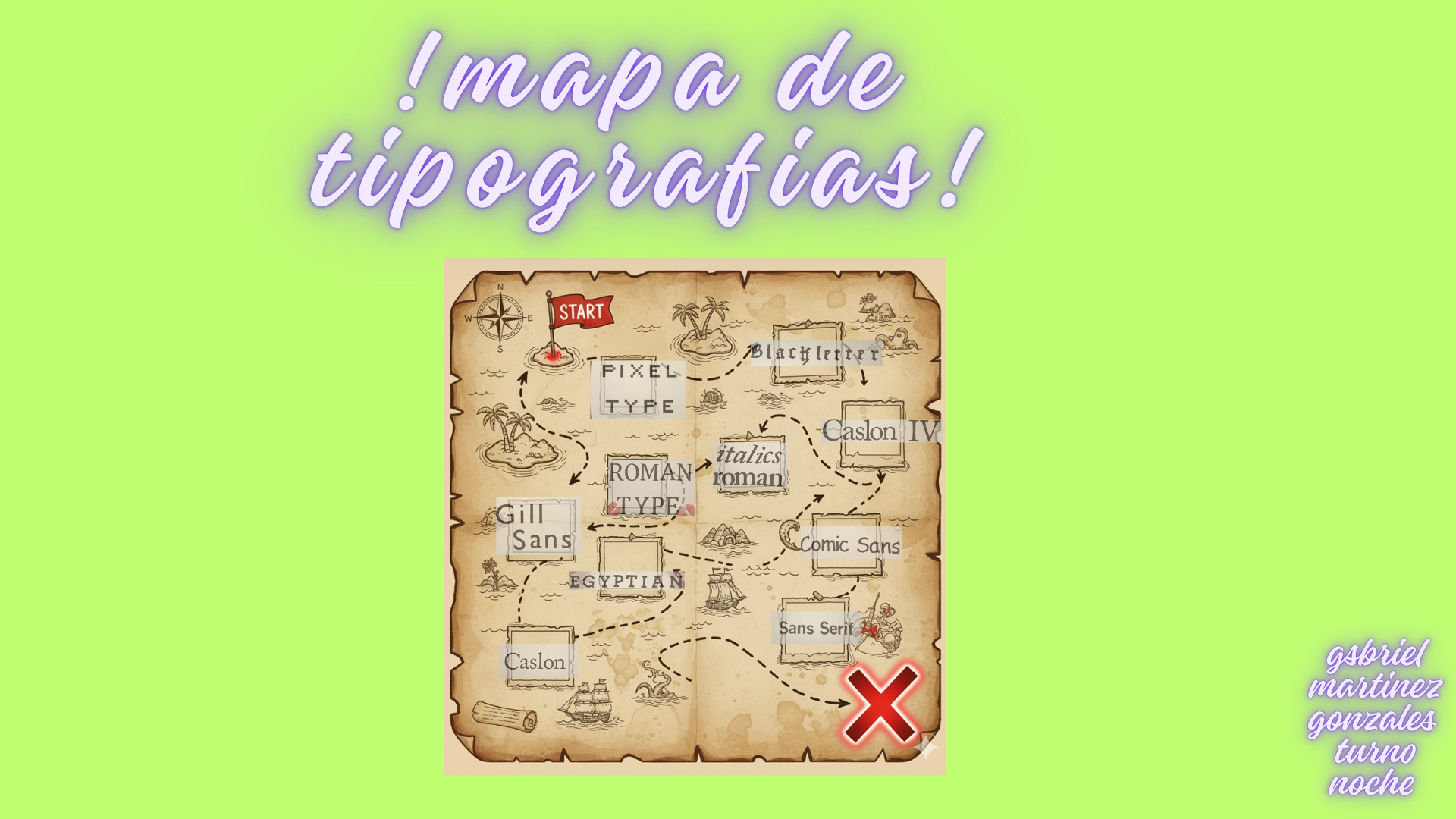
Mapa de tipografias
explora la historia de las tipografias , conoce mas sobre ellas
1 pixel type 2 blackletter 3 caslon IV 4 Italics roman 5 Roman type 6 Gill sans 7 Egyptian 8 comic sans 9 caslon 10 sans serif
Explicación
una de las primeras fuentes digitales
europa occidental
Nieto de caslon I
en manuscritos medievales
en las mayusculas de la antigua roma
1928
Gran bretaña
vincent connare
si , diseñado en metal
si, en 1816